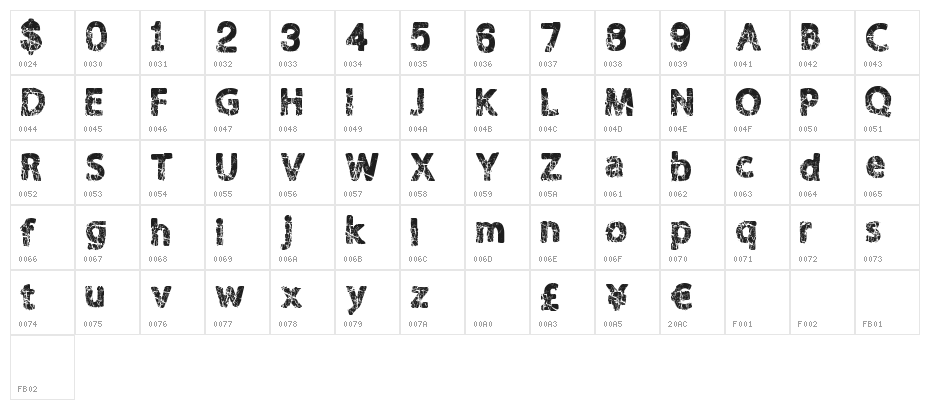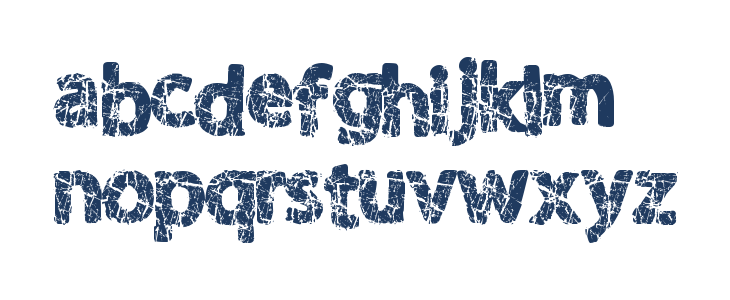
Shaken Font
| Gesamtstil | Grunge, Urban, Distressed |
| Vorgeschlagene Projekte | Ideal for music album covers, posters, edgy branding, and urban-themed designs. |